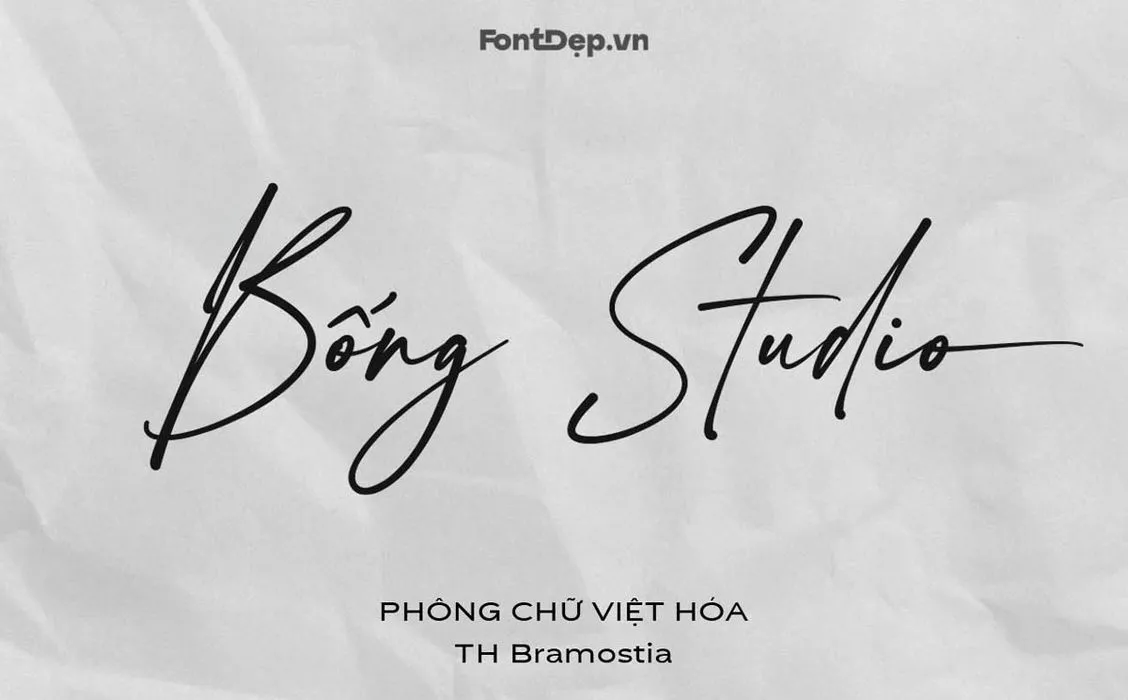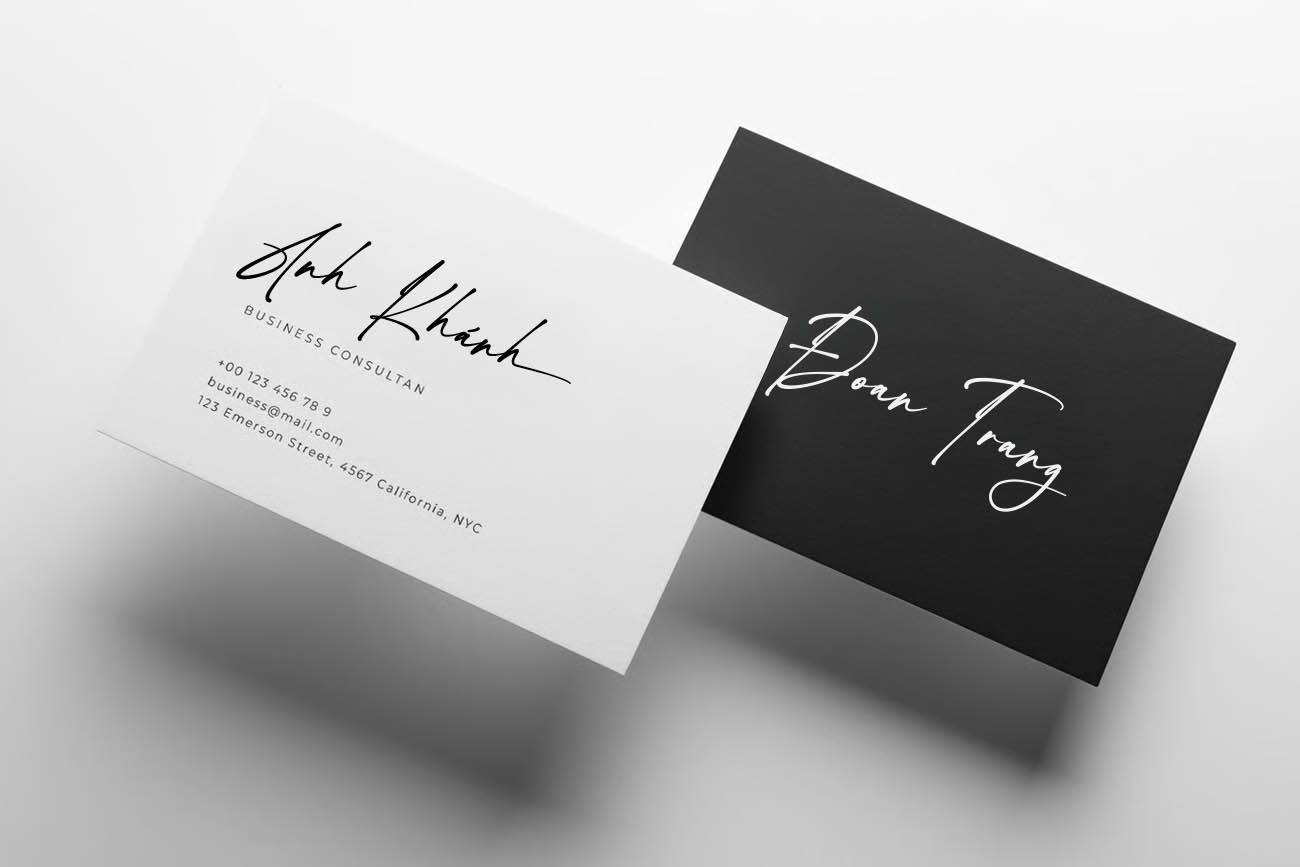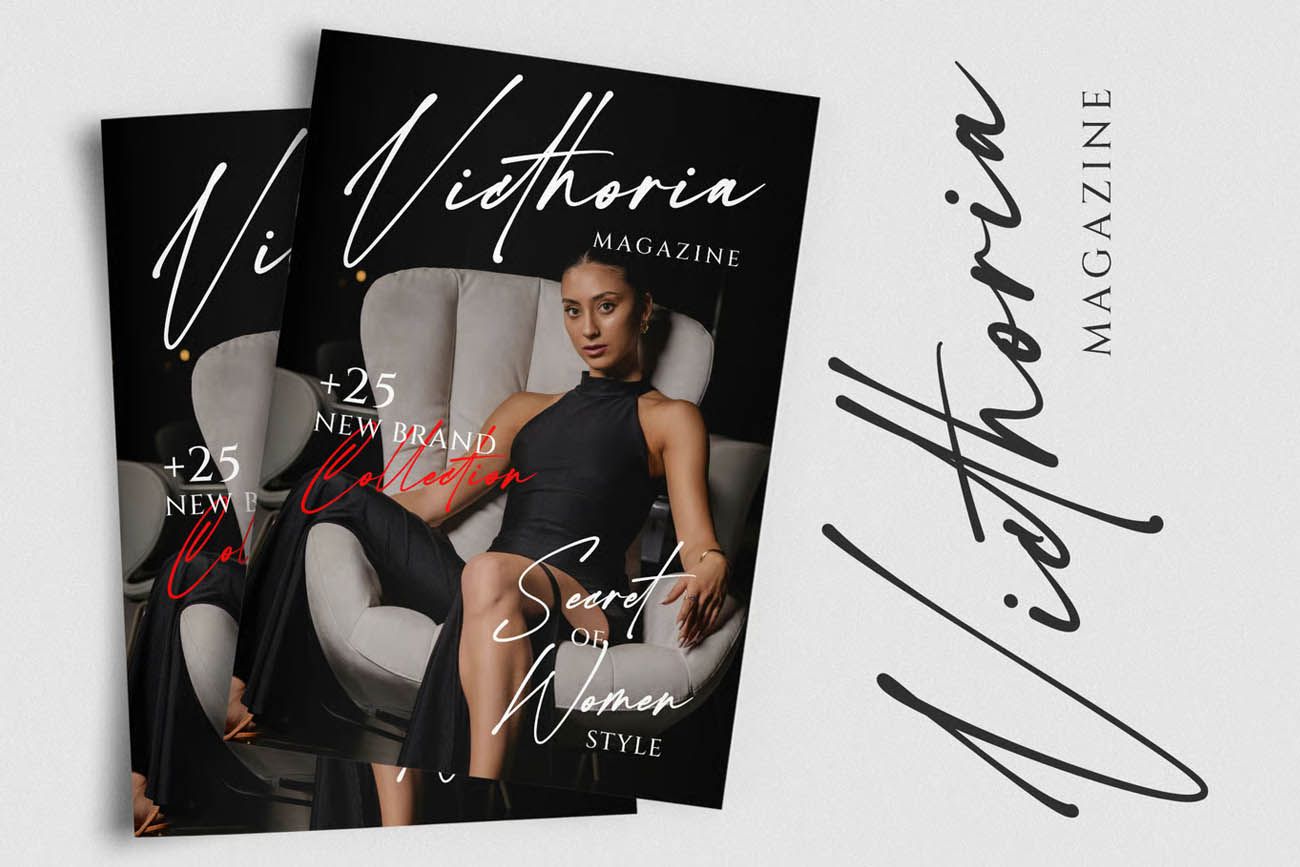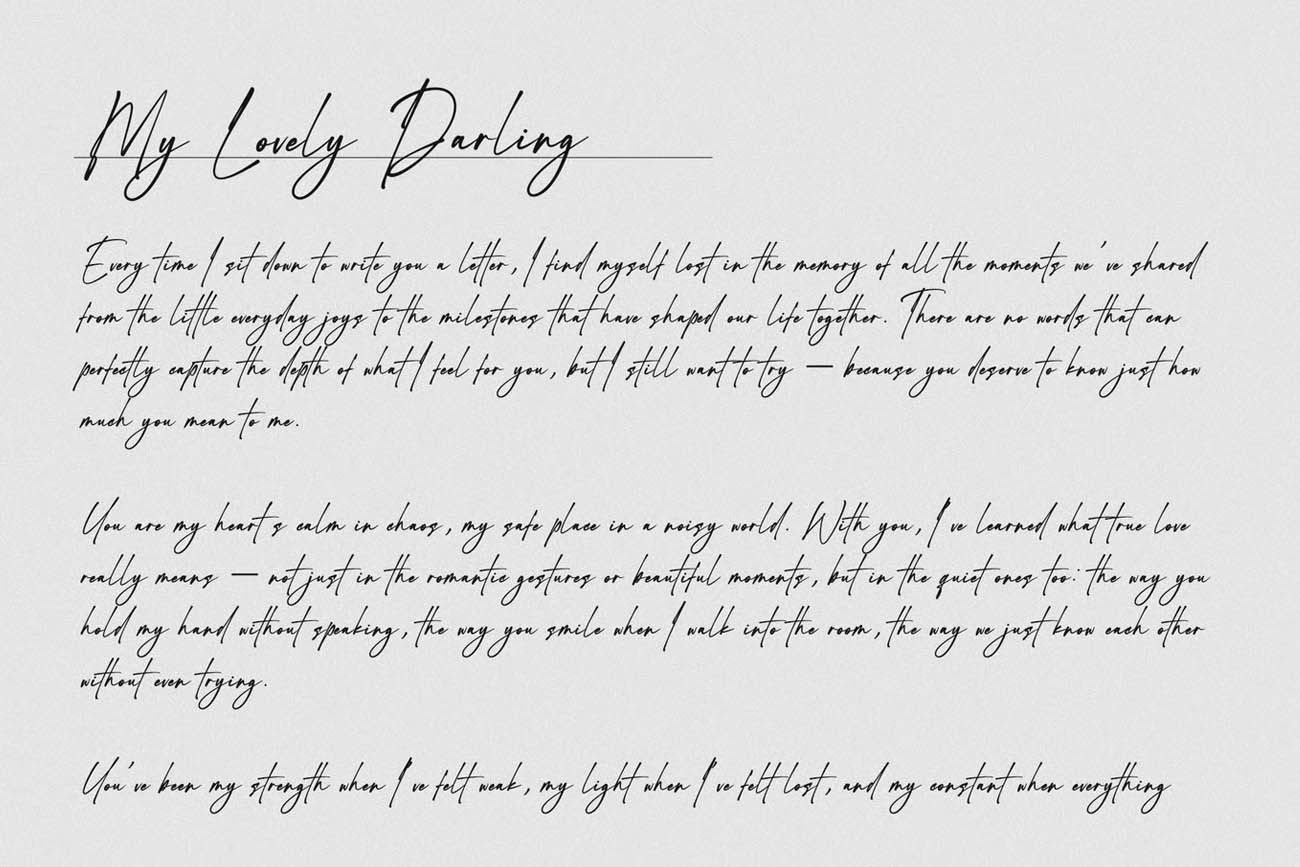
Nếu bạn đang cần một kiểu chữ giống như nét bút tay – mềm mại, tự nhiên và có chút gì đó cá nhân – thì Bramostia Việt hóa là một lựa chọn rất đáng thử. Font này được thiết kế theo kiểu chữ ký viết tay, trông vừa đơn giản nhưng vẫn giữ được sự tinh tế và đẹp mắt.
Bramostia là sản phẩm của StringLabs Creative Studio – một nhóm thiết kế đến từ Indonesia, chuyên làm các font chữ viết tay có cảm xúc. Font được tạo ra với mục đích mô phỏng chữ ký tự nhiên: hơi nghiêng nhẹ, nét mảnh, có nhịp điệu và rất “có hồn”.
Điểm mình thích nhất ở Bramostia là nhìn chữ rất tự nhiên, không bị cứng hay khuôn mẫu. Dù bạn dùng để viết tên thương hiệu, chèn chữ ký lên ảnh, hay ghi lời nhắn trên thiệp mời – font này đều thể hiện rất tốt. Nhìn vào là thấy sự mềm mại, chân thật.
Font đã được Phạm Sơn – Admin Fontdep.vn & S99.vn Việt hóa lại, có đầy đủ dấu tiếng Việt, không bị lỗi ký tự như nhiều font nước ngoài. Bạn có thể dùng ngay trong Photoshop, Canva hay bất kỳ phần mềm thiết kế nào mà không cần chỉnh sửa gì cả. Ngoài ra, Bramostia còn có thêm nhiều chữ thay thế (alternates), giúp bạn làm chữ không bị đều mà vẫn trông tự nhiên, sinh động.
Tóm lại, nếu bạn đang tìm một font chữ ký Việt hóa đẹp, dễ dùng và mang phong cách riêng, thì Bramostia là một lựa chọn không nên bỏ qua. Dùng thử một lần là dễ “dính” luôn đấy!